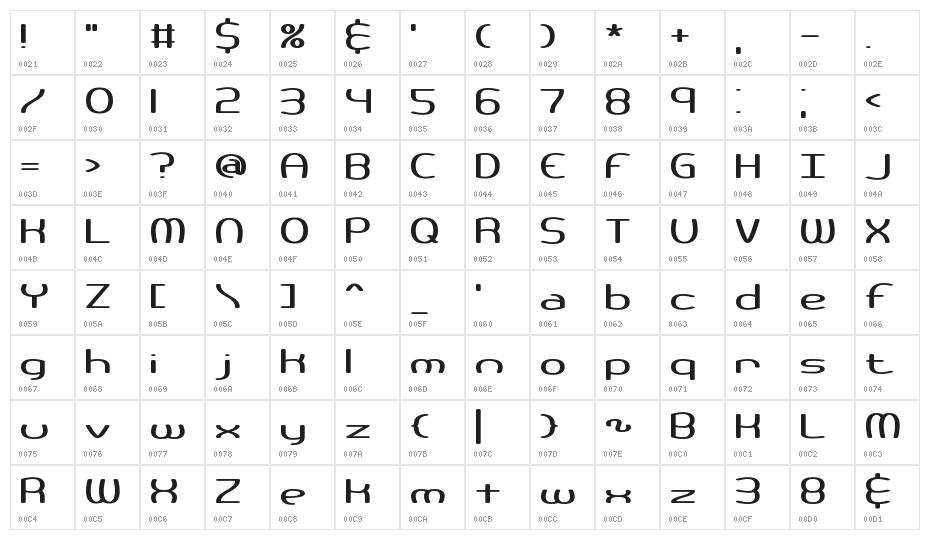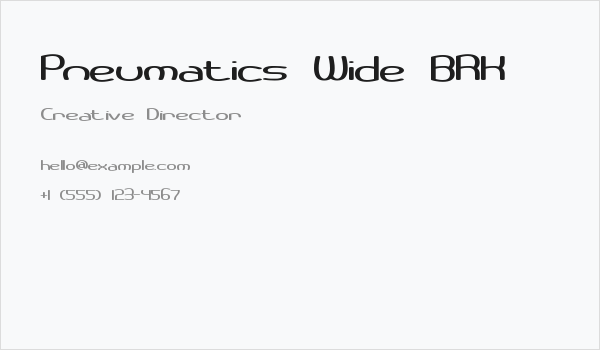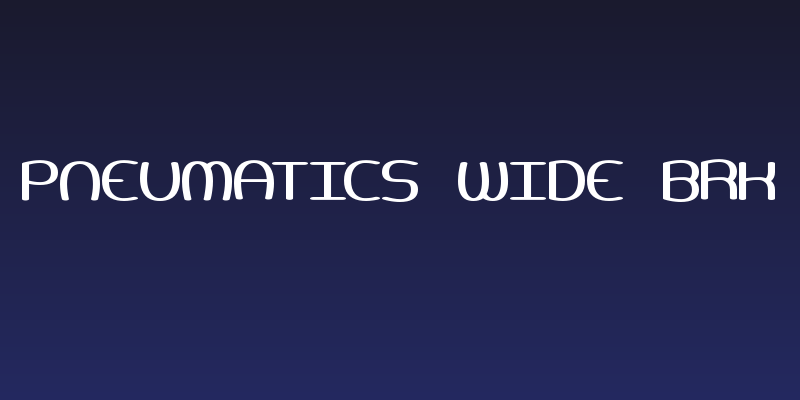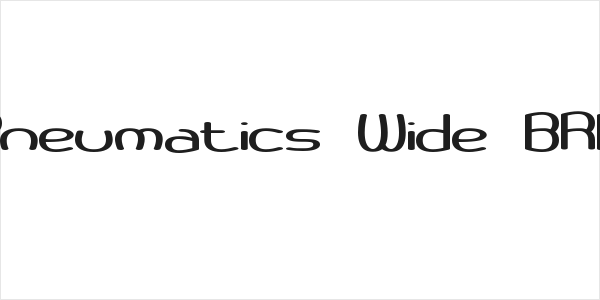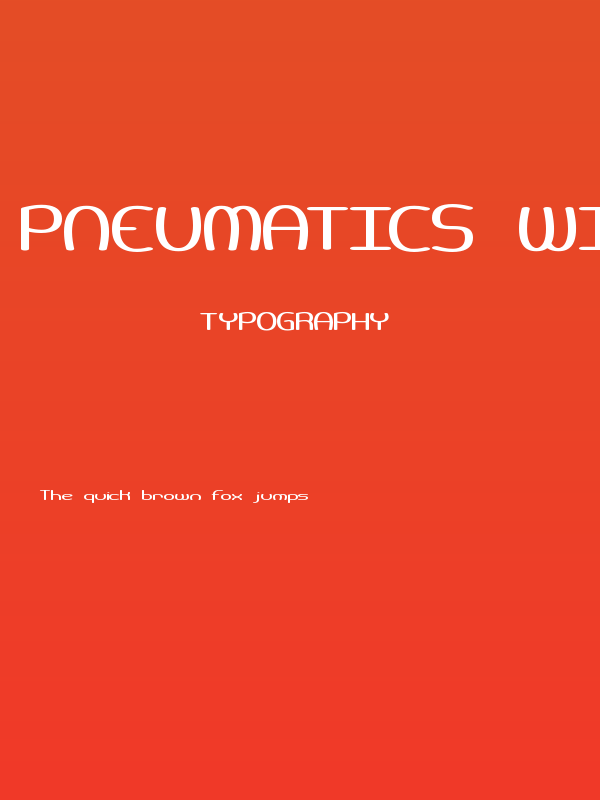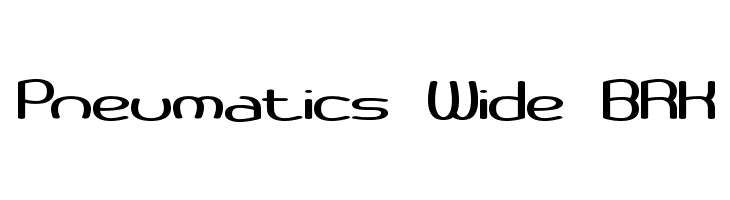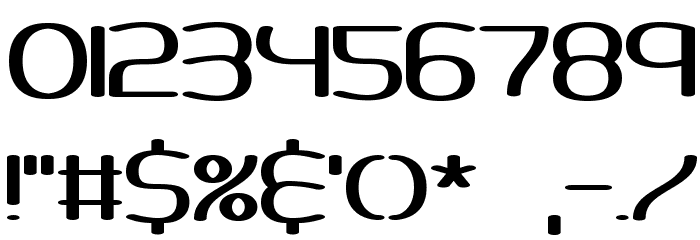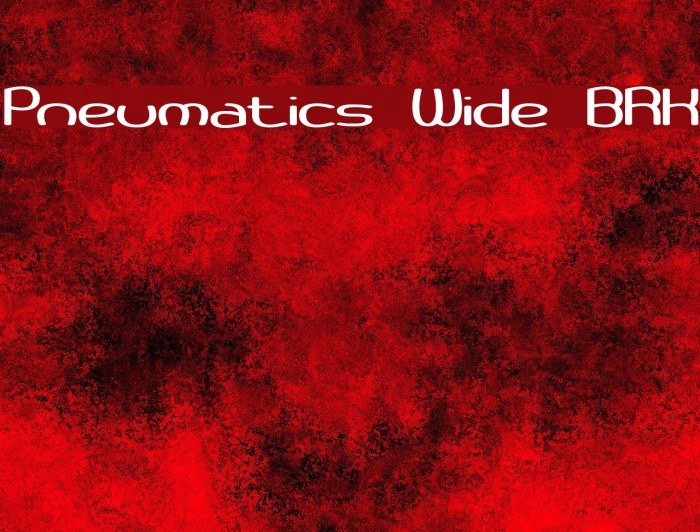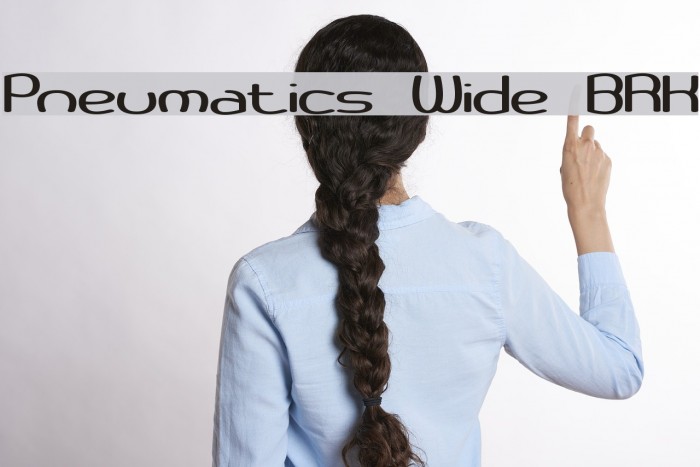
Pneumatics Wide BRK Font
✎ Round
| Categorie | Round |
| Larghezza | Expanded |
| Progetti proposti | Ideal for branding, advertising, posters, and digital media projects that require a modern and distinctive look. |